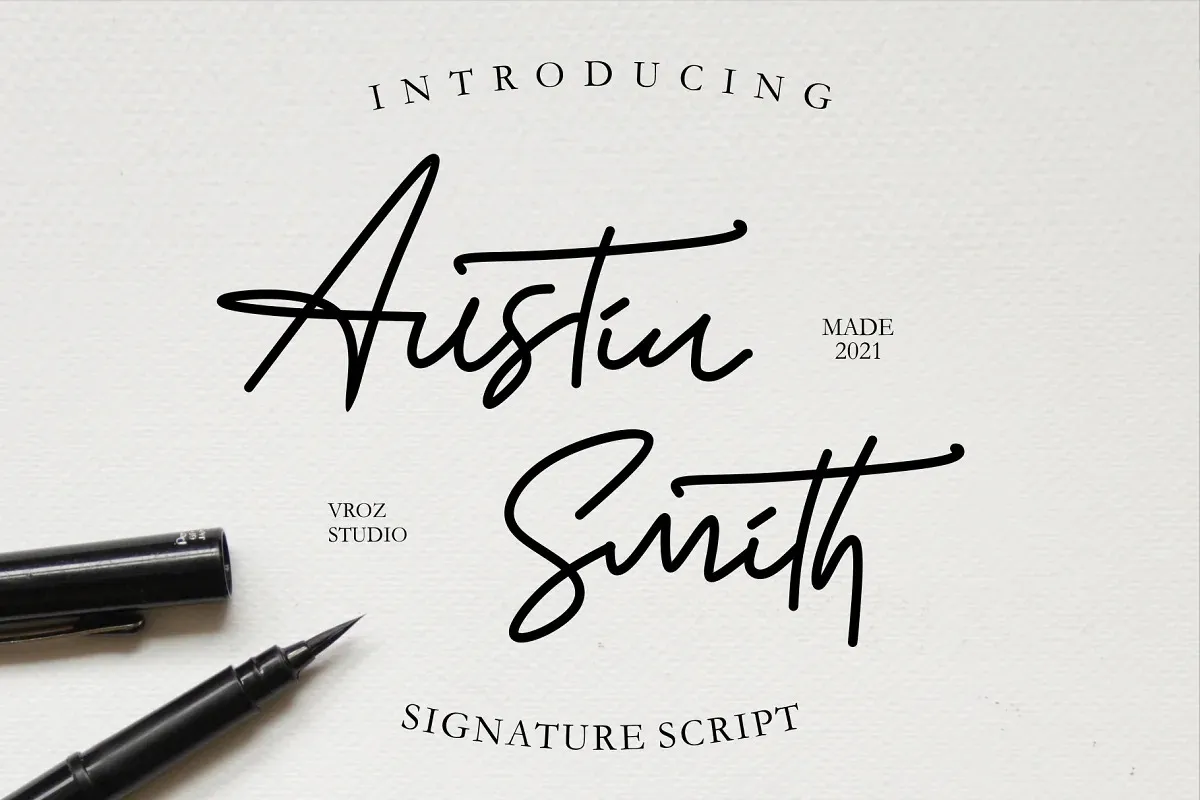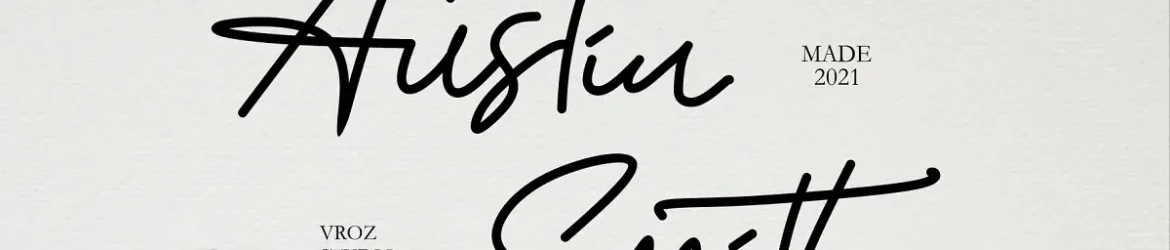
Austin typeface – Download Grátis
A Austin Typeface é uma delicada fuente escrita a mão que traz ao design uma sensação cálida e romântica. Ela vem do designer Vroz Studio, onde encontramos a Austin Smith Signature Script, uma fonte perfeitamente adequada para diversas necessidades de criação gráfica. A Austin Smith Signature Script é ideal para estilizar marcas ou assinaturas de forma moderna e sofisticada, desde invitações de casamento até embalagens de produtos e campanhas promocionais. Esta fuente moderna mantém um toque autêntico no seu design, proporcionando aos designers uma opção perfeita para se conectar com seus trabalhos mais pessoais ou românticos. Além disso, você terá toda a combinação de letras minúsculas e maiúsculas, números e sinais de pontuação disponíveis, o que lhe dá flexibilidade na hora de criar qualquer tipo de layout. É uma escolha versátil para estilos variados, garantindo um visual harmônico em qualquer projeto.